Các mẫu logo nail đẹp, bí quyết chọn màu sắc, font chữ chuẩn
Các mẫu logo nail đẹp giúp salon nail tạo ấn tượng mạnh và ghi nhớ thương hiệu trong mắt khách hàng. Việc lựa chọn màu sắc, font chữ và phong cách thiết kế phù hợp là yếu tố quan trọng để logo nổi bật. Bài viết tổng hợp những màu sắc, font chữ phổ biến và xu hướng thiết kế logo nail hiện nay.
Vì sao màu sắc và font chữ quan trọng trong thiết kế logo nail?
Màu sắc và font chữ không chỉ thể hiện cá tính thương hiệu mà còn ảnh hưởng trực tiếp đến cảm nhận của khách hàng. Logo nail cần nổi bật, dễ nhận diện và phù hợp với phong cách dịch vụ.
Việc chọn màu và font đúng giúp logo trở nên sang trọng, hiện đại hoặc nữ tính, tùy hướng đi của salon nail. Đồng thời, màu sắc còn tác động đến cảm xúc: màu pastel tạo cảm giác nhẹ nhàng, màu nóng nổi bật và thu hút, màu tối sang trọng và chuyên nghiệp.
Màu sắc thường được chọn cho logo nail
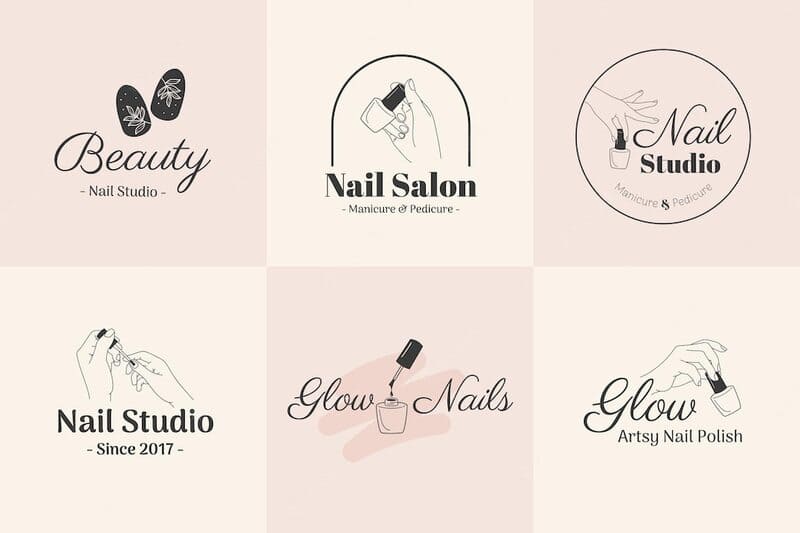
Màu sắc thường được chọn cho logo nail
Mỗi salon nail có thể lựa chọn màu sắc khác nhau để thể hiện thương hiệu. Một số màu phổ biến gồm:
- Hồng pastel và nude: Tạo cảm giác dịu dàng, nữ tính, gần gũi với đa số khách hàng nữ.
- Đỏ, cam, vàng: Thu hút sự chú ý, thể hiện sự nổi bật và năng động.
- Tông đen trắng: Sang trọng, chuyên nghiệp, dễ phối với mọi nền thiết kế.
- Màu kim loại (vàng, bạc, đồng): Sang trọng, thích hợp cho logo cao cấp và thương hiệu đắt giá.
Lựa chọn màu sắc phù hợp giúp logo nail nổi bật trên nền tảng truyền thông, đồng thời phản ánh đúng phong cách salon, từ nhẹ nhàng, sang trọng cho đến cá tính và hiện đại.
Font chữ phù hợp trong thiết kế logo nail
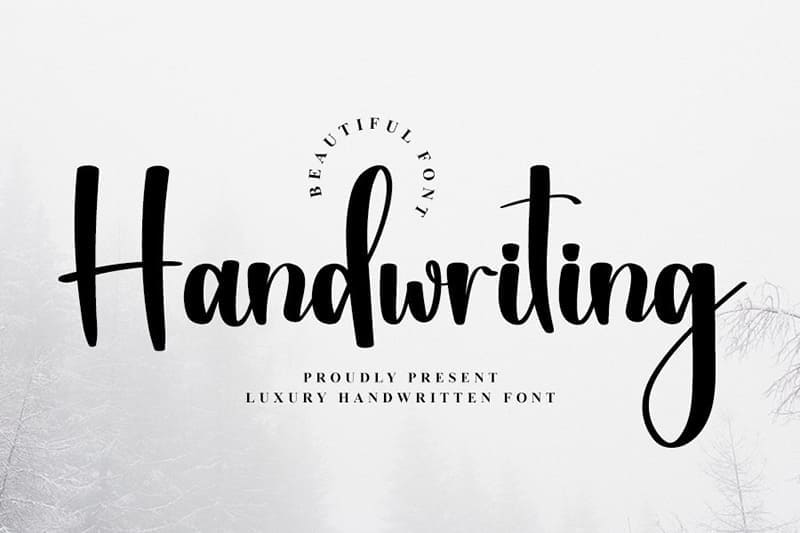
Font chữ phù hợp trong thiết kế logo nail
Font chữ góp phần thể hiện cá tính và thông điệp thương hiệu. Một số xu hướng font chữ thường được sử dụng:
- Font script hoặc handwriting: Mang lại cảm giác mềm mại, nữ tính, phù hợp với salon nail hướng đến khách hàng nữ.
- Font sans-serif hiện đại: Gọn gàng, rõ ràng, dễ đọc, phù hợp với phong cách trẻ trung, năng động.
- Font serif sang trọng: Thể hiện sự chuyên nghiệp và đẳng cấp, phù hợp các salon nail cao cấp.
- Font kết hợp (script + sans-serif): Tạo điểm nhấn, vừa mềm mại vừa hiện đại, giúp logo dễ nhớ và nổi bật.
Lựa chọn font chữ phù hợp giúp logo dễ đọc, ấn tượng, đồng thời phản ánh đúng cá tính thương hiệu và hướng khách hàng mục tiêu.
Top 8 các mẫu logo nail đẹp để tham khảo
Dưới đây là 8 mẫu logo nail đẹp, thể hiện cách phối màu và font chữ hiệu quả, có thể áp dụng cho salon của bạn:
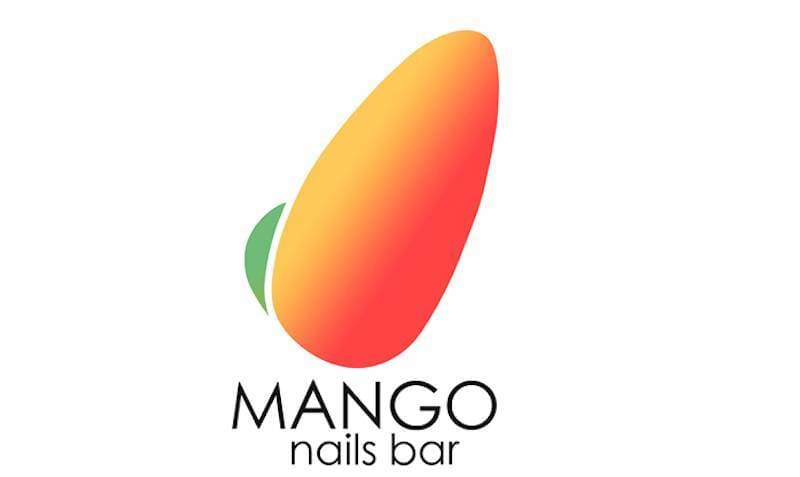
Logo Nail độc đáo hình móng tay cách điệu giống quả xoài theo tên cửa hàng
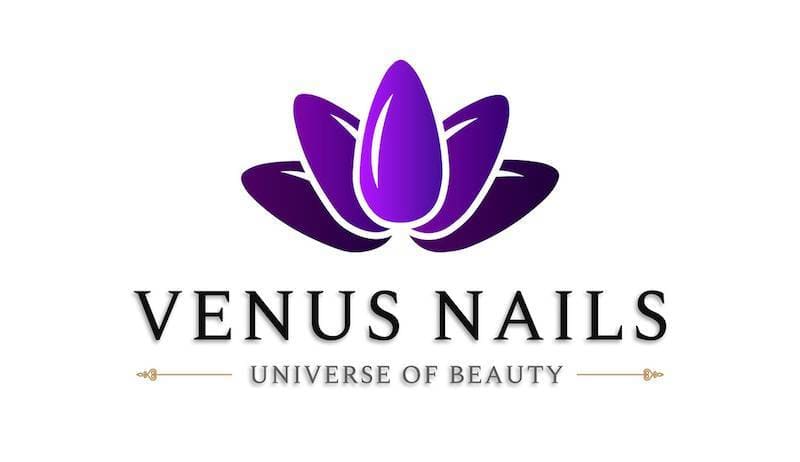
Biểu tượng móng tay kết hợp thành bông sen tạo nên logo ấn tượng cho tiệm Nail
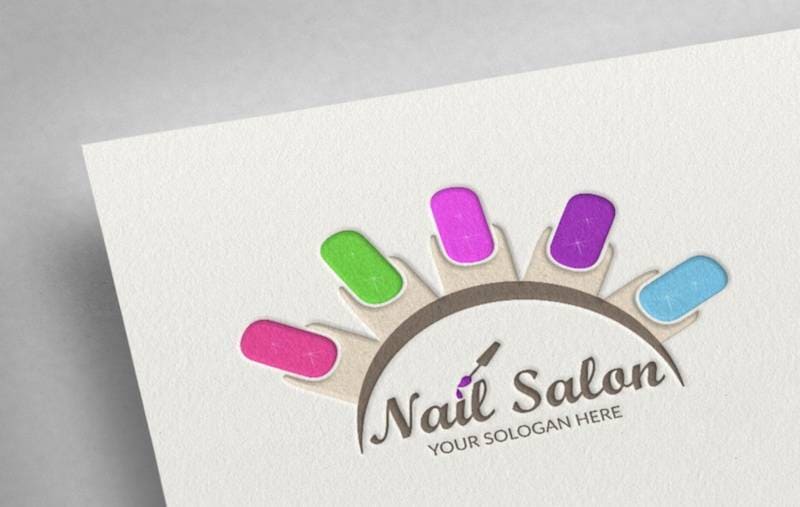
Logo tiệm nail đẹp với hình ảnh móng tay đầy màu sắc trẻ trung và năng động
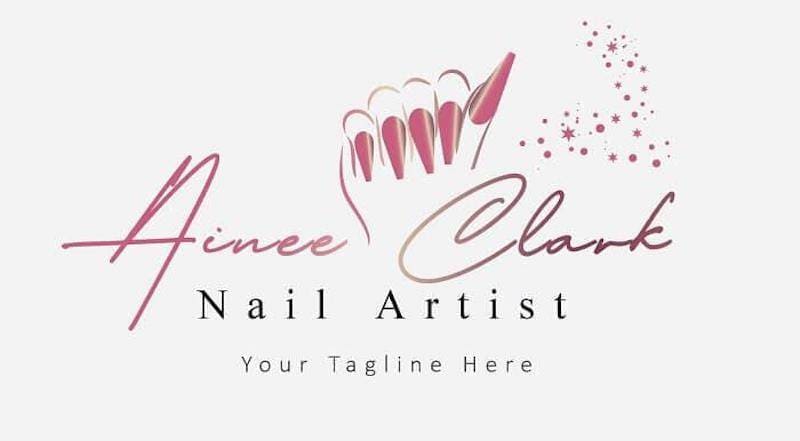
Mẫu thiết kế logo tiệm Nail hình bàn tay cách điệu tone hồng
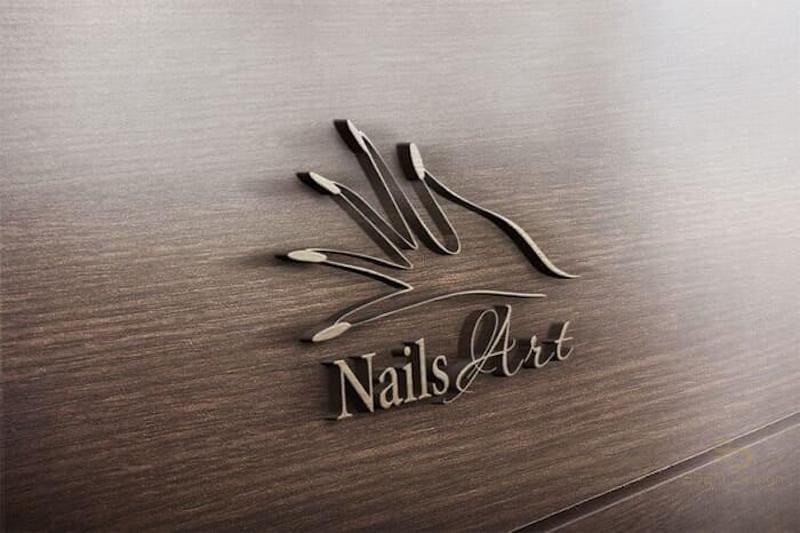
Hình ảnh Logo bàn tay đơn giản nhưng hiện đại dành cho tiệm Nail
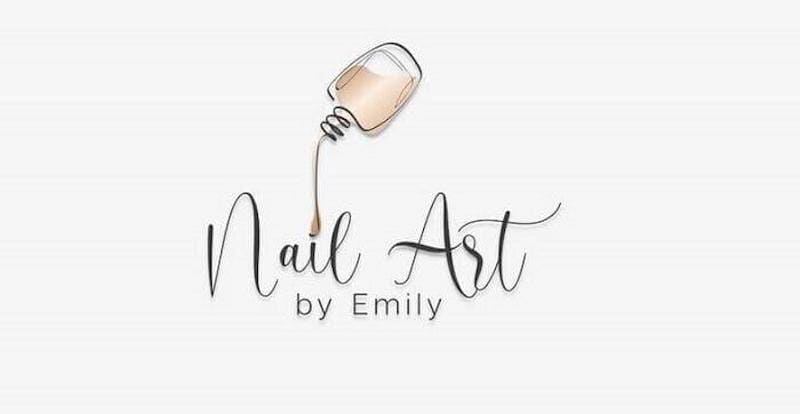
Logo tiệm Nail đẹp cách điệu lọ sơn móng tay đổ xuống
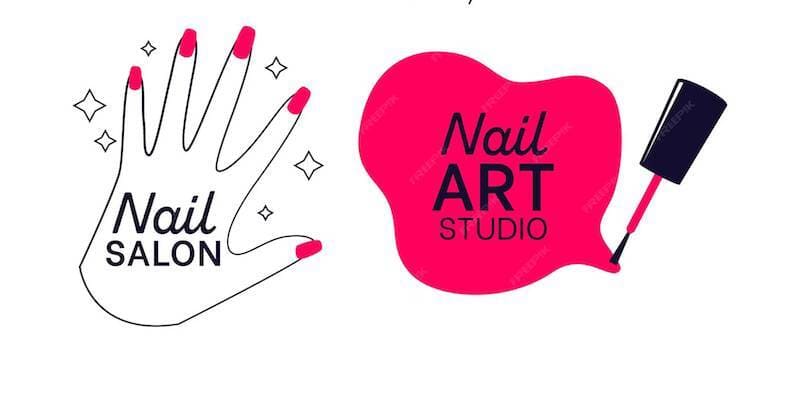
Logo tiệm Nail sử dụng biểu tượng lọ sơn móng tay là hình ảnh thường gặp
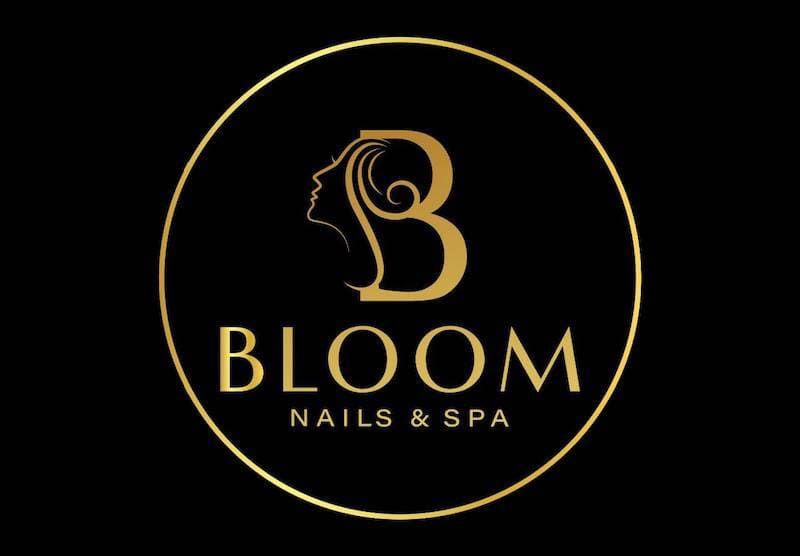
Logo hình cô gái cách điểm thể hiện sự nữ tính, tinh tế và thời trang
Các mẫu trên là sự kết hợp giữa màu sắc, font chữ và biểu tượng nail để tạo logo dễ nhận diện, sang trọng và ấn tượng. Salon nail có thể dựa vào các mẫu này để phát triển thương hiệu riêng, phù hợp với khách hàng mục tiêu.